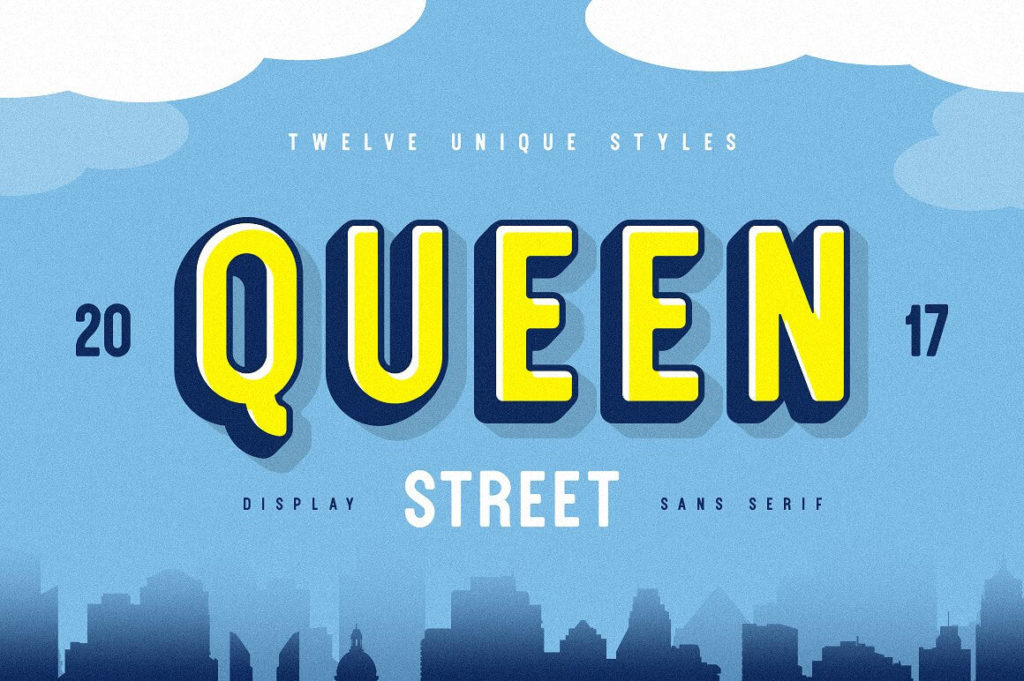
Шрифт Queen Street Display
это выразительный гротеск в стиле винтажного дисплейного шрифта от студии **Vintage Type Company**, выпущенный в 2017 году. Вдохновленный ручной росписью и резьбой по дереву на вывесках старых бутиков, он обладает характерным «слоистым» (stackable) дизайном, позволяющим создавать объемные эффекты путем наслоения начертаний. Это современный взгляд на ретро-стилистику, идеально подходящий для создания заголовков, логотипов и акцентных элементов в кириллических текстах. Шрифт поддерживает базовую кириллицу (включая русский язык) и расширенную латиницу с множеством диакритических знаков, что делает его универсальным инструментом для международных проектов